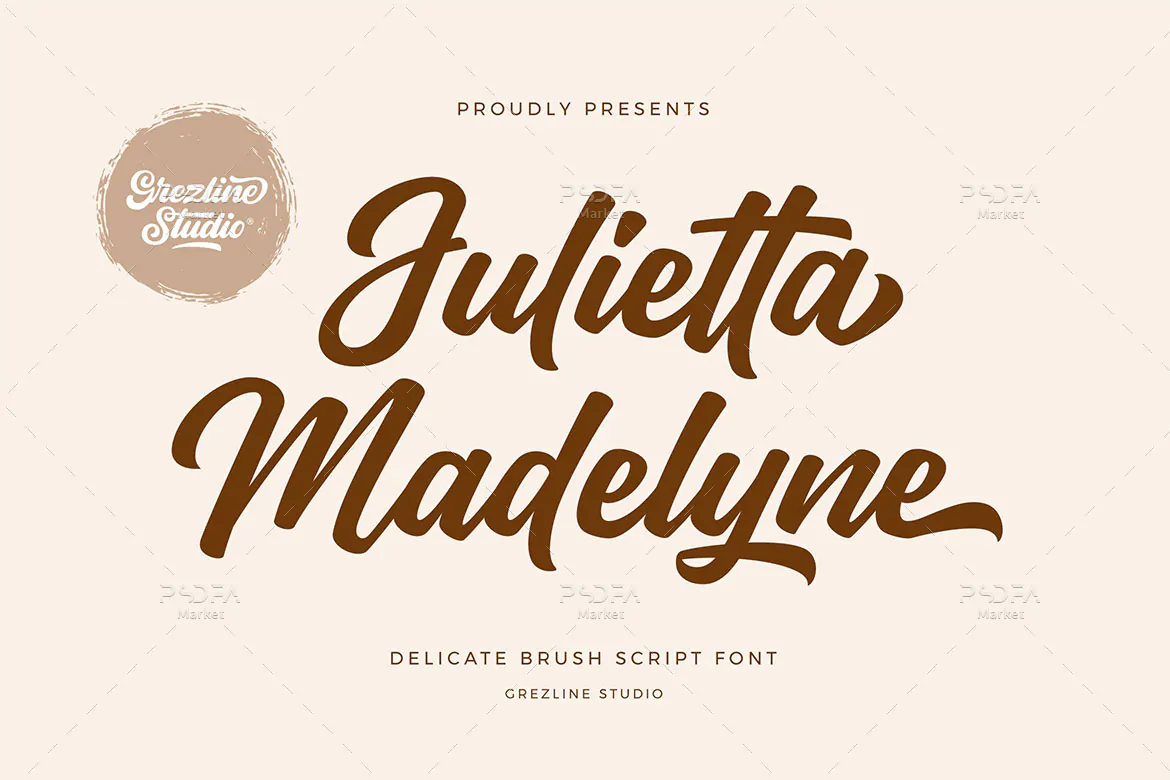
اسکریپت فونت ظریف Julietta Madelyne
اسکریپت فونت ظریف
اسکریپت فونت ظریف Julietta Madelyne یک قلم انگلیسی دستنویس فوق العاده زیبا است که مناسب جهت استفاده در طرح و پروژه‌های گرافیکی مختلف می‌باشد. فونت Julietta Madelyne با وزن معمولی طراحی شده است که می‌توانید از آن در طراحی پوستر، کارت تبریک، طرح‌های ولنتاین، بسته بندی محصولات، تیشرت، ظروف یکبار مصرف و … می‌باشد.